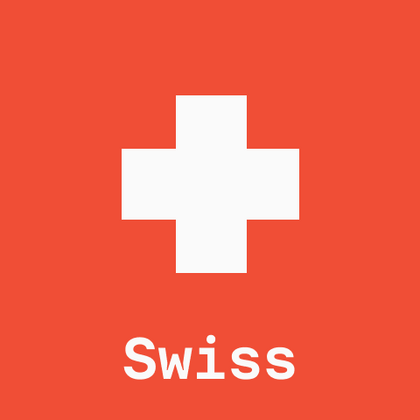
Подборка Швейцарских шрифтов
Для проектов, требующих безупречной типографической дисциплины, наша подборка про Швейцарские шрифты предлагает гарнитуры с математически выверенными пропорциями и расширенными языковыми поддержками. Каталог TypeType включает шрифты, сохраняющие принципы швейцарского стиля: универсальность применения и визуальную ясность в любых размерах.
Каждый из представленных шрифтов содержит Швейцарский алфавит. Широкий выбор символов, знаков валют и пунктуации, шрифтовых начертаний и OpenType фич позволят применять один шрифт для разных проектов. Знаки расширенной латиницы, содержащие диакритические знаки, расширят возможности использования шрифта для разных стран.